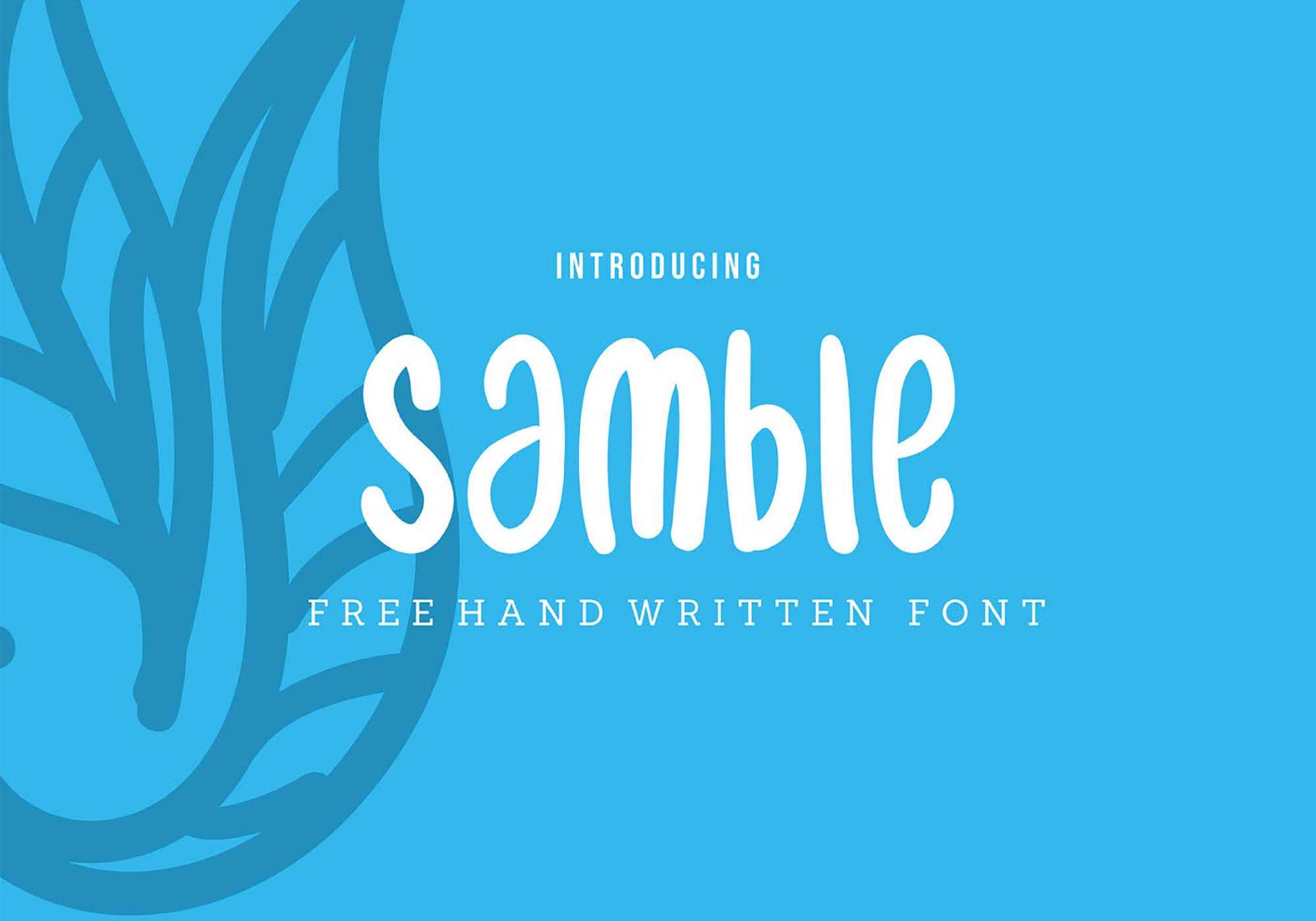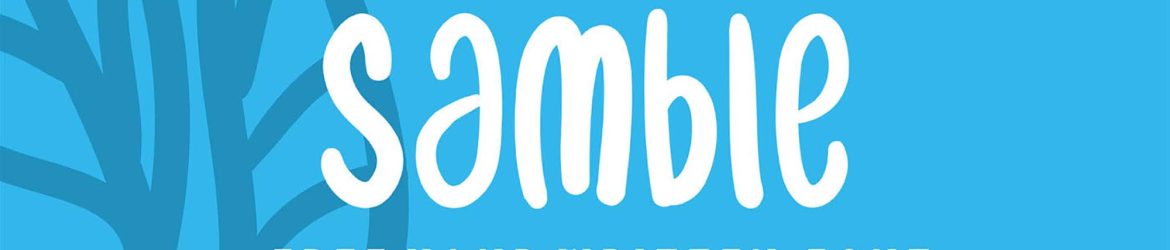
Samble Playful Handwritten Font – Download Grátis
A fonte ‘Samble Playful Handwritten Font’ captura a essência da arte humana, quebelecamente capturada em cada letra e traço. Esta fonte, embora não seja uma criação manual, transmite a autenticidade e a graça do desenho natural. Seu estilo elegante e despojado permite que você crie desde textos pequenos e impressionantes até soluções de problemas grandiosas. Em um mundo onde o design gráfico e digital está sempre em evolução, ‘Samble Playful Handwritten Font’ oferece uma escolha visual única, combinando a essência do retrato humano com a precisão do mundo digital. Seja você um designer, um influenciador digital ou mesmo um criador de conteúdo para redes sociais, esta fonte pode ser a chave para transformar suas ideias em algo realmente impressionante.